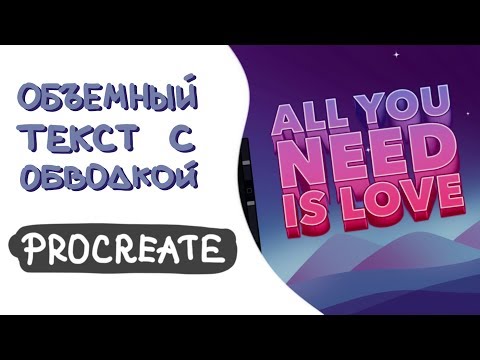
Идеи для создания шрифтов с обводкой и придания им особого стиля
Шрифты с обводкой являются популярным способом придать тексту дополнительную выразительность и эффектность. В этой статье вы найдете полезные советы и идеи о том, как создать шрифты с обводкой и сделать их особенными.
Используйте контрастные цвета для обводки и основного шрифта, чтобы создать эффектную комбинацию.
Экспериментируйте с толщиной обводки, чтобы найти идеальное сочетание между читабельностью и выразительностью.
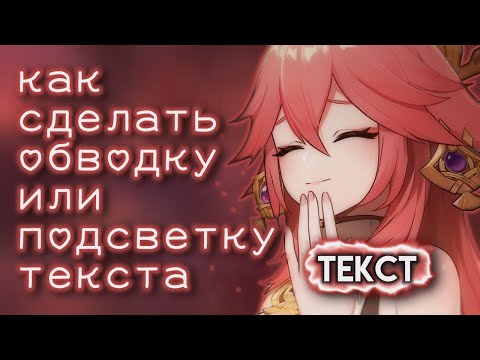
Добавьте дополнительные эффекты, такие как тень или градиент, чтобы усилить визуальное воздействие шрифта.